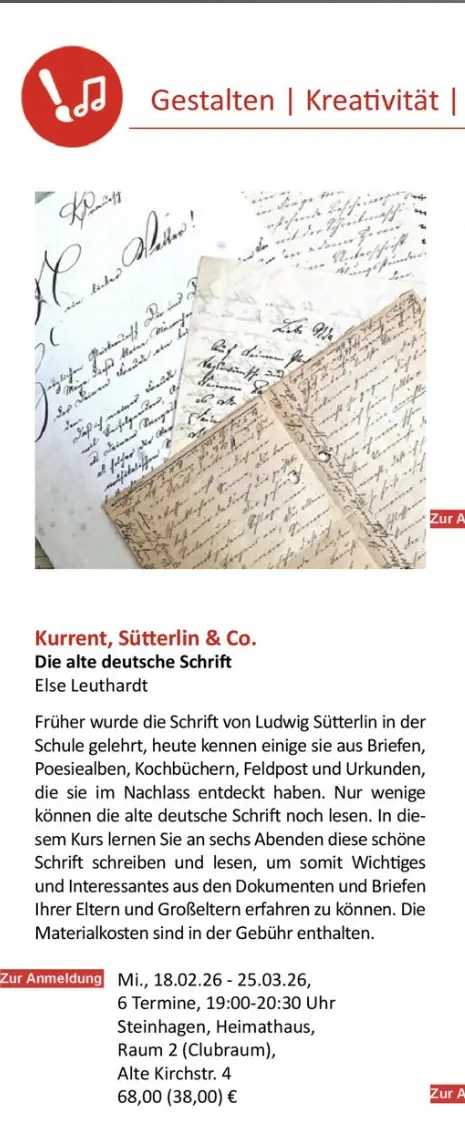
Kurrent - Sütterlin & Co.
Früher wurde die Schrift von Ludwig Sütterlin in der Schule gelehrt, heute kennen einige sie aus Briefen, Poesiealben, Kochbüchern, Feldpost und Urkunden, die sie im Nachlass entdeckt haben. Nur wenige können die alte deutsche Schrift noch lesen. In diesem Kurs lernen Sie an sechs Abenden diese schöne Schrift schreiben und lesen, um somit Wichtiges und Interessantes aus den Dokumenten und Briefen Ihrer Eltern und Großeltern erfahren zu können. Die Materialkosten sind in der Gebühr enthalten.